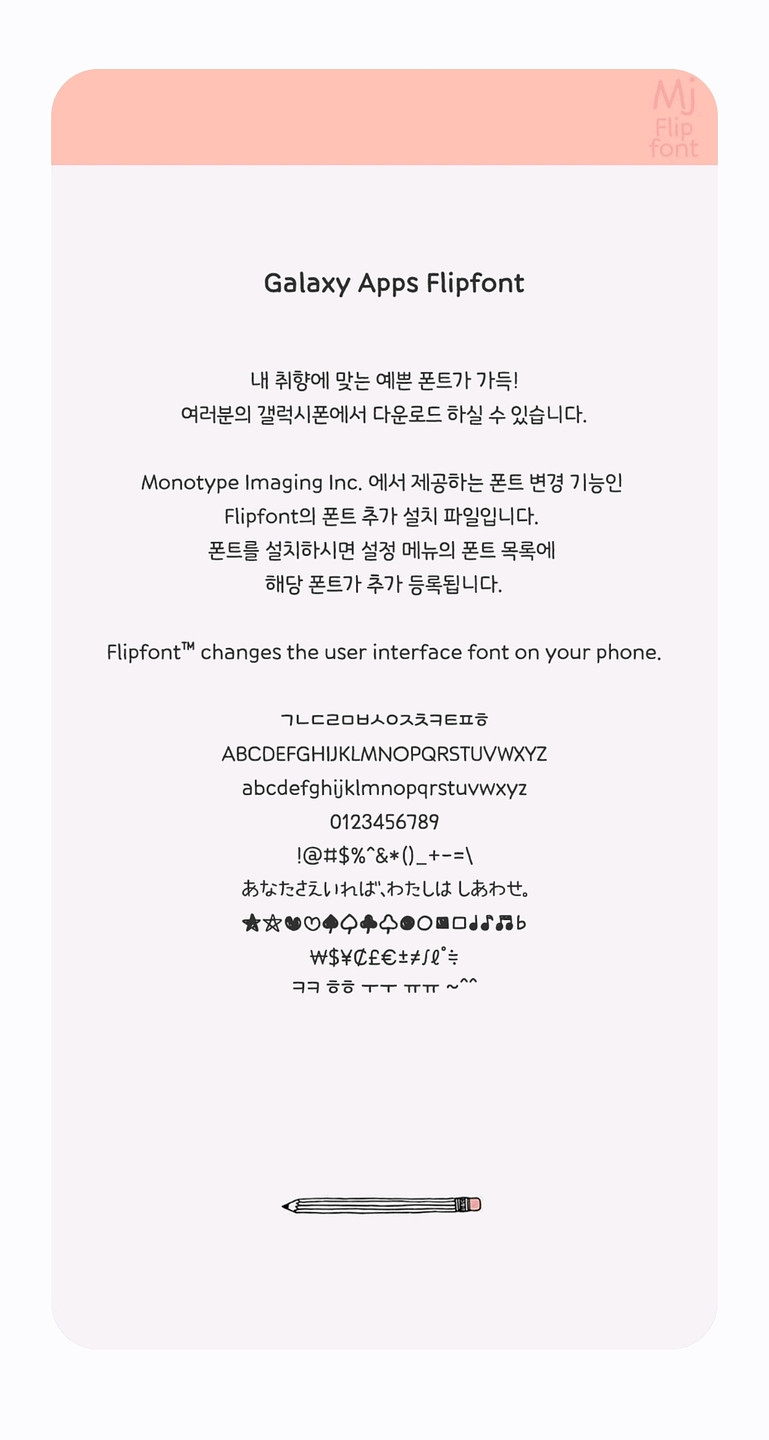
예전에도 질문했었는데 여기저기 검색해도 못찾아서 다시 올립니다ㅜㅜ! 삼각형 특수문자도 조금 특이한데, 이 폰트는 대체 뭘까요?ㅠㅠ 너무 알고 싶습니당ㅠㅠㅠ 헉! 알려주셔서 정말 감사드립니다
Mj연필산스
이거 맞을까요? 친구가 쓰는 폰트랑 똑같은 것 같아서 친구한테 물어보고 알려드립니다 ! 특수문자도 직접 색칠한 듯한 느낌을 줘서 특이하게 보이는 것 같아요